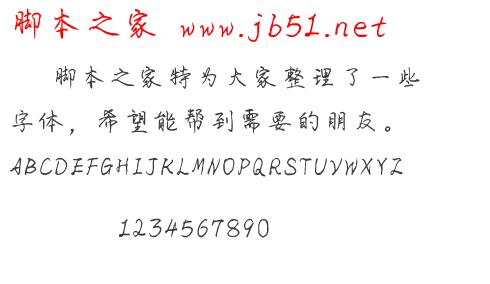
玉平手寫體是一款非常漂亮的藝術(shù)字體,玉平手寫體字體廣泛用于各種書刊、畫冊(cè)的設(shè)計(jì)印刷中,玉平手寫體字體具有強(qiáng)烈的視覺沖擊力,報(bào)紙和雜志和書籍中常用字體, 海報(bào)、個(gè)性促進(jìn)品牌標(biāo)志設(shè)計(jì)、字體設(shè)計(jì)、等環(huán)境。